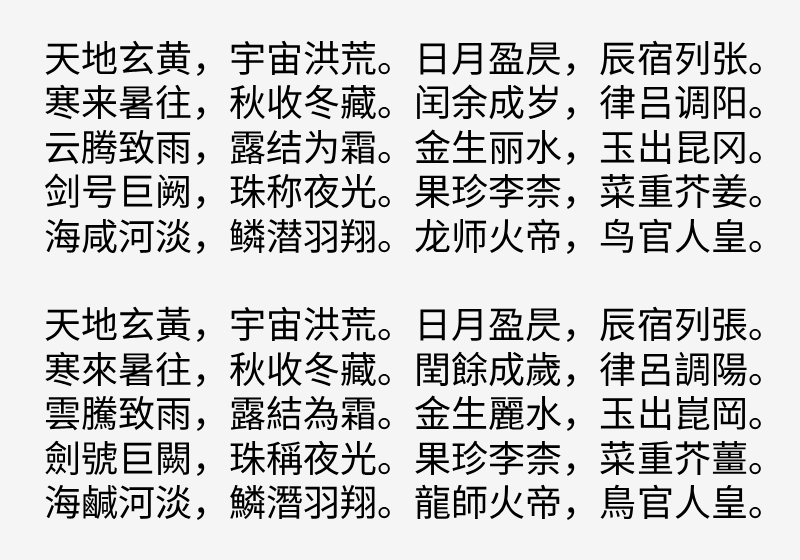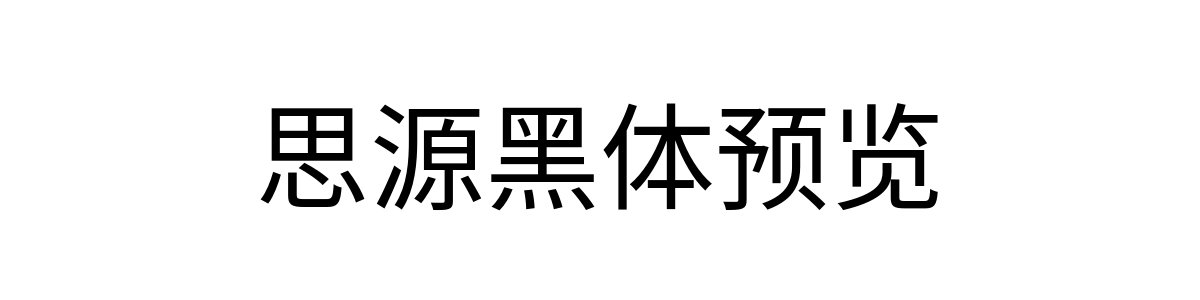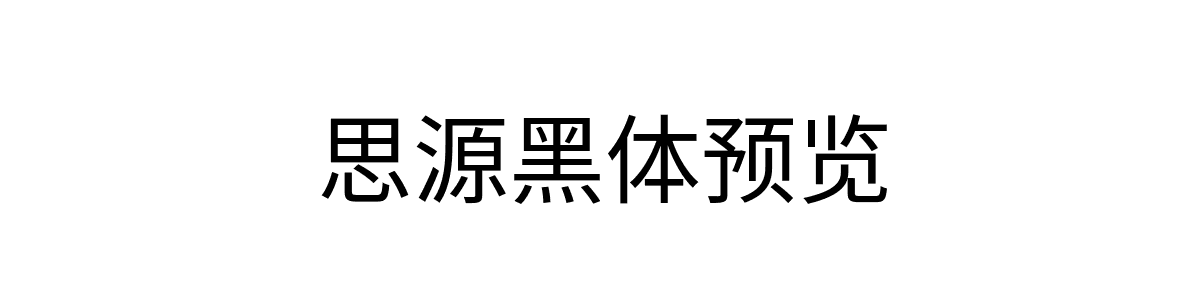
思源黑体
思源黑体(Source Han Sans / Noto Sans CJK)是 Adobe 与 Google 历时三年时间,于2014年7月发布推出的一款开源字体,是史上首个真正意义上的泛 CJK 字体。
这款字体支持简体中文、繁体中文、日文韩文,同时包含完整的拉丁字符集,覆盖了超过65000个字符,整个字体家族的字形个数接近50万,是目前最完善的免费商用字体之一。
思源黑体的开发以 Adobe 的设计师西冢凉子为主导,其西文及数字采自 Source Sans Pro 字体,汉字部分则分别以各语种为基础,由不同设计公司制作——日文为 Iwata、中文为常州华文、韩文为 Sandoll 等,其字形皆依循各国国家标准。
思源黑体的风格介于现代和传统之间。其设计目标是可以广泛用于多种用途的计算机字体,比如用于手机、平板、或者桌面的用户界面、网页浏览或者电子书阅读等。